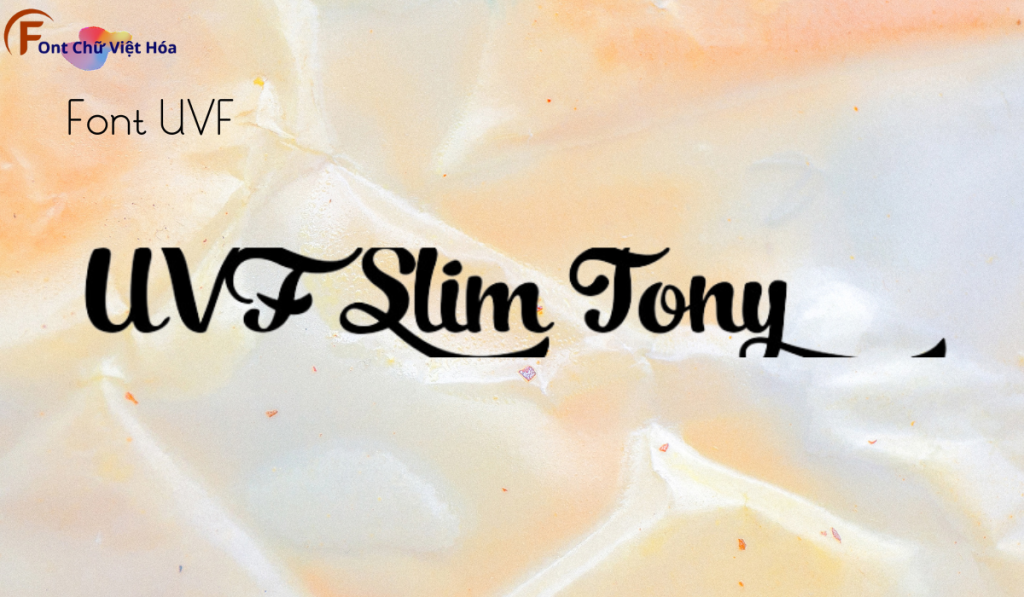
Font UVF Slim Tony Việt Hóa
Tác giả: Không rõ tác giả
Bộ Font: UVF
Kiểu chữ: Sans-serif
UVF Slim Tony Việt Hóa là font sans-serif với các đường nét thanh thoát và hiện đại, thuộc bộ font UVF. Font này được thiết kế nhằm mục tiêu tạo ra sự rõ ràng và dễ đọc, đặc biệt phù hợp cho các thiết kế như poster, logo, và tiêu đề. Đặc điểm hình dạng của UVF Slim Tony là các đường nét mảnh mai và tỷ lệ chữ cân đối, giúp tối ưu hóa không gian và tạo ấn tượng thị giác mạnh mẽ. Font này cũng đã được Việt hóa, mang đến sự linh hoạt và tiện dụng cho các dự án thiết kế bằng tiếng Việt, giúp người dùng dễ dàng tiếp cận và sử dụng.